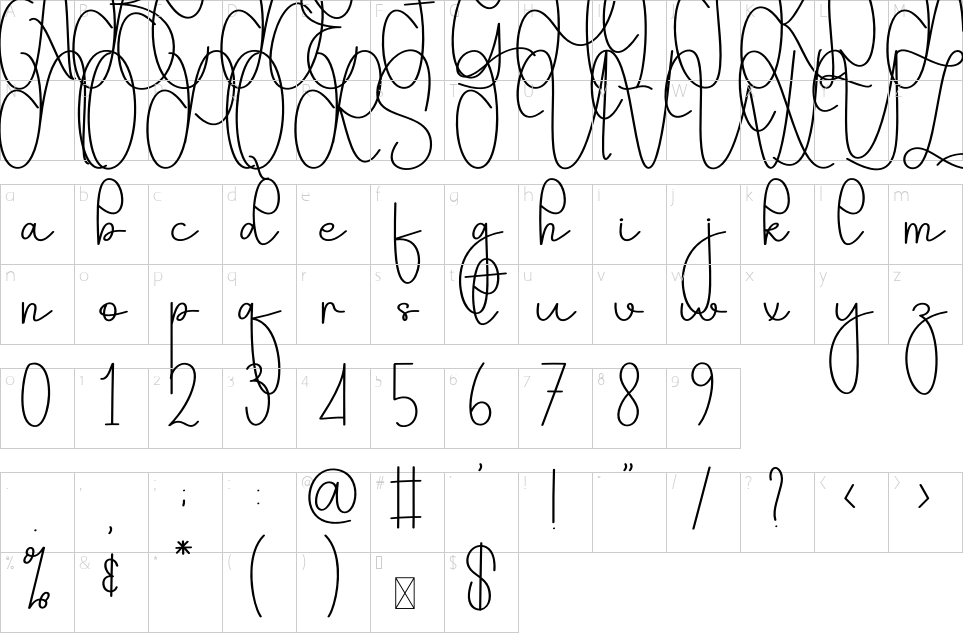
A Delightful Font é uma opção incrível para quem está procurando por uma fonte agradável para projetos pessoais ou profissionais. Desenvolvida pelo designer William Jhordy, esta elegante e versátil fonte pode ser usada em qualquer sistema operacional – seja Windows ou Mac. A Delightful Font foi projetada com um toque leve e encantador que certamente vai enriquecer seu design. Com 238 downloads já realizados, é evidente o quanto ela se destaca entre as muitas opções disponíveis. Se você está procurando por uma fonte para dar um toque especial ao seu trabalho, a Delightful Font pode ser uma escolha ótima.